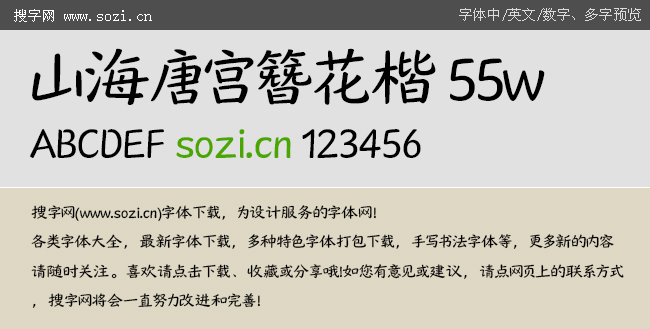
山海唐宫簪花楷 55w
搜字网给大家提供一款山海唐宫簪花楷 55w中文字体下载,山海唐宫簪花楷是一款全新的楷体字体,该字体字形优美文雅,禅韵内敛,取楷体细腻的书写笔画,书法的运笔走势蕴含其中,流畅自然,蕴含东方审美韵味,尽显优雅从容,秀雅清新,禅韵十足。适用于画册设计、海报设计、包装设计等场合使用。